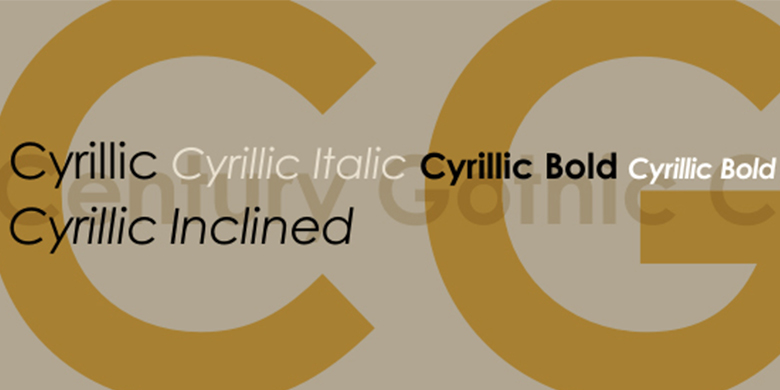
Century Gothic是在1936年至1947年间由Sol Hess绘制的Monotype 20th Century的基础上而创作的。Century Gothic保留了20th Century的基本设计,但x高度增加了,而且为了确保使现代数字系统的输出令人满意而对其进行了修改。该设计受到了在20世纪二三十年代特别流行的几何风格的无衬线字体的影响。Century Gothic字体家族可用于标题和常规显示工作以及少量文本,尤其是在广告中。
Century Gothic is based on Monotype 20th Century, which was drawn by Sol Hess between 1936 and 1947. Century Gothic maintains the basic design of 20th Century but has an enlarged x-height and has been modified to ensure satisfactory output from modern digital systems. The design is influenced by the geometric style sans serif faces which were popular during the 1920s and 30s. The Century Gothic font family is useful for headlines and general display work and for small quantities of text, particularly in advertising.